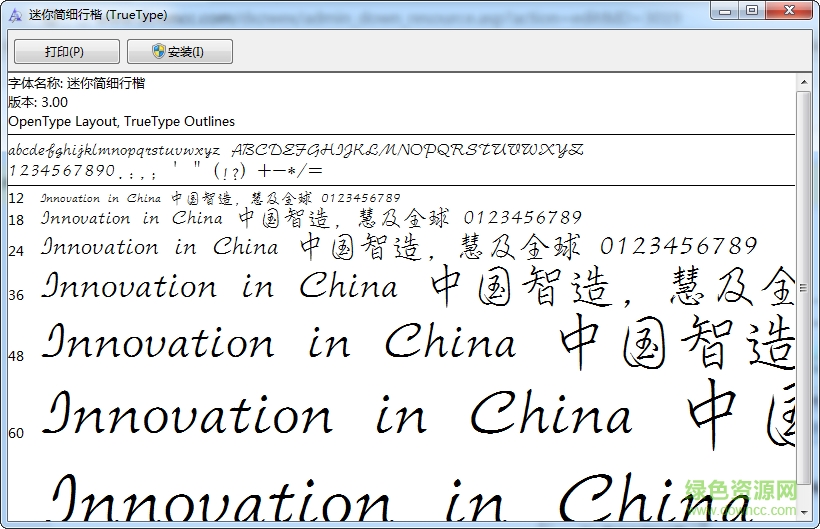
jxixinkai細(xì)行楷字體
jxixinkai是什么字體?jxixinkai字體就是迷你簡細(xì)行楷體,筆畫纖細(xì),線條非常流暢靈活,結(jié)構(gòu)比起楷書字體更為松散,美觀又實用,讓你書面所書寫的字體更加有特色,還能與你的朋友共享該字體哦,需要行楷字體的朋友快來下載吧!
行楷字體介紹
行書是各種字體中最為流行的,之所以流行而長盛不衰,因其所具有的實用性和一定的隨意性。它又可分為行楷、行草兩類。我們習(xí)慣上把介于楷書與行書之間的字體稱為行楷。
行楷書寫特點
行楷的用筆則靈活、方便,一般不需要逆鋒、頓筆、停筆等嚴(yán)格的運筆,不強調(diào)用筆中更多的提按、筆畫形態(tài),只要求筆道流暢,使轉(zhuǎn)合理,行筆巧妙。